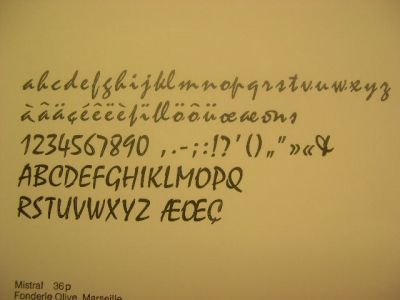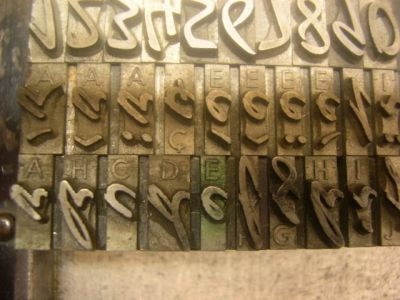
Schaut mal.. eine Mistral
Das ist eine französische Schreibschrift mit Namen Mistral von der Fonderie Olive, Marseille. Entworfen hat sie Roger Excoffon im Jahr 1954.
Bemerkenswert weitsichtig:
Solche einer Handschrift nachempfundenen Bleisatz-Schriften sind sehr schwer zu setzen. Die Gemeinen n, u und v sind einander ungemein ähnlich.
Die Schriftgießer haben eine ganz simple Hilfe genutzt:
Unter die Schriftlinie der Gemeinen ist in Versalien jeweils die Art des Letters erhaben mitgegossen - genial.
P.S. Fällt jemandem von Euch am Andruck etwas auf?
Uups.. nein. Das ist nur ein Flüchtigkeitsfehler. Die 4 p Durchschuß fehlen. Das meinte ich nicht.
Ich wage auch mal einen Versuch:
Das ß fehlt (das kann aber auch am Andruck liegen?), dafür gibt es ein langes s (hinter dem è oder deute ich das falsch?) und ein geschwänztes z und ein s für Wortenden.
Alles in allem finde ich die Schrift ganz schön.
die Lösung ist so einfach, daß Ihr gar nicht darauf kommen könnt.
Denn wenn Ihr ein Versal-J oder ein Versal-N braucht, dann drückt Ihr einfach noch einmal auf die entsprechende Taste der Tastatur.
Im Bleisatz ist jeder Letter nur in sehr begrenzter Anzahl vorhanden. Und wenn das J und das N fehlen, ist der Schriftschnitt... nur noch Schrott.
Aber diese Schrift ist so selten, daß ich sie ausnahmsweise dennoch gedruckt habe. Obwohl JEDEM Fachmann aus dem Graphischen Gewerbe natürlich SOFORT ins Auge springt, daß bei den Versalien eben diese Lettern fehlen: J und N.